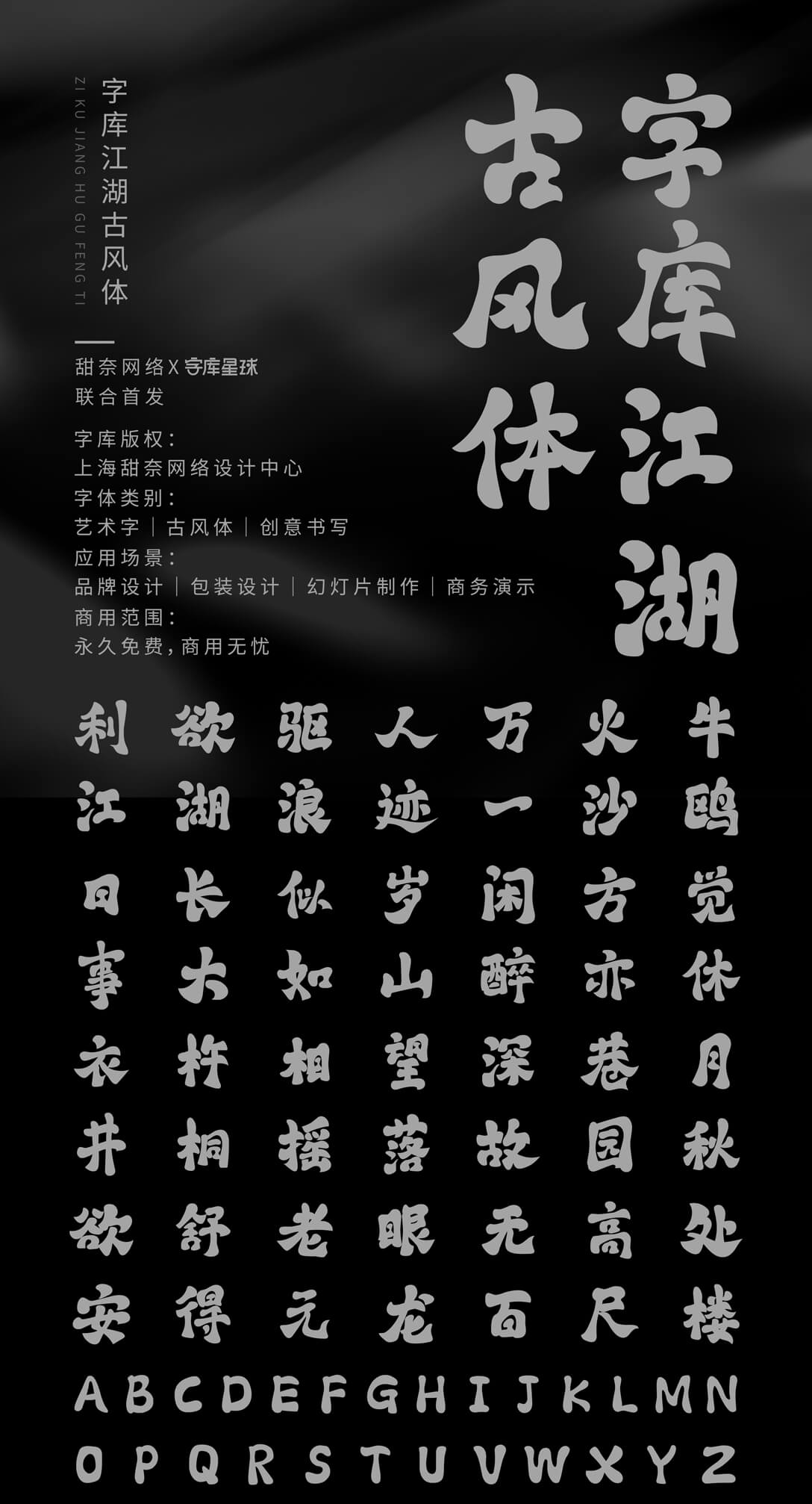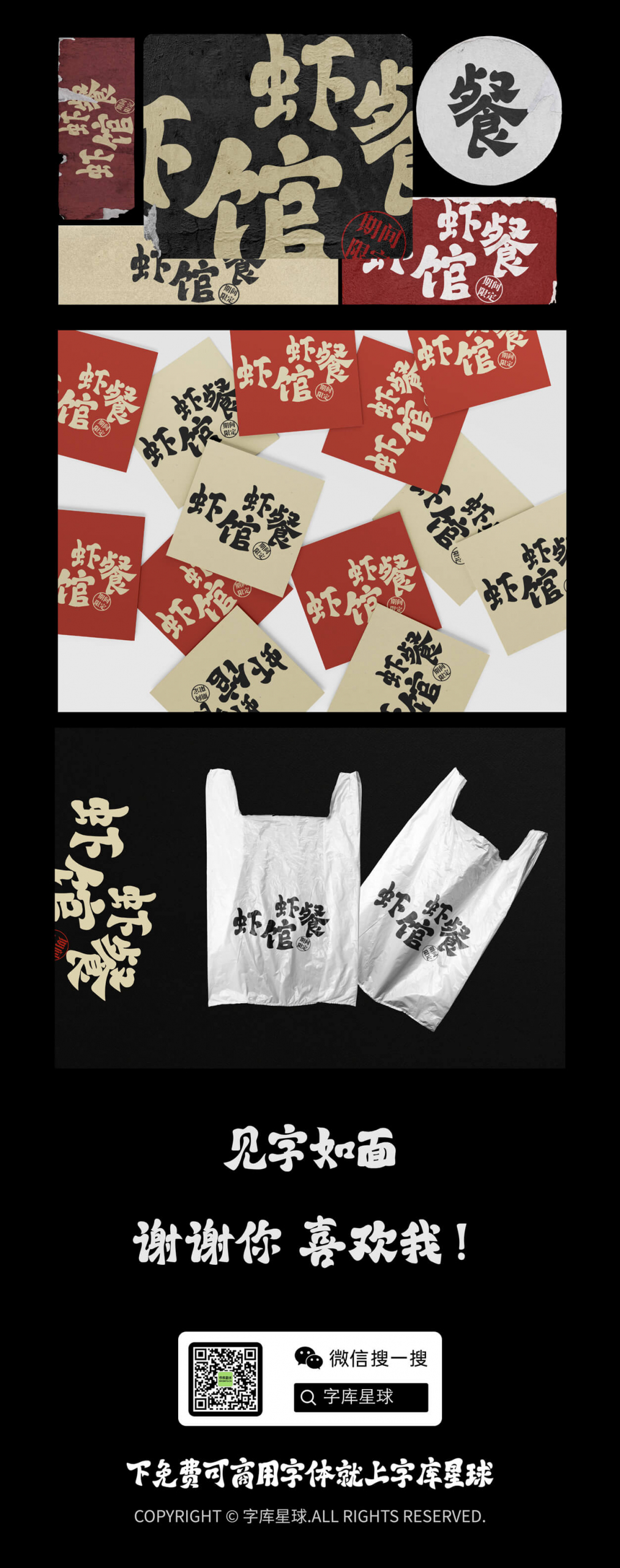
时光飞逝,不知不觉间,字库星球已悄然走过一年的旅程。身为设计师,想必大家的字库都囤积了琳琅满目的字体,可真正派上用场的却寥寥无几。首当其冲的便是恼人的字体侵权难题,在各大设计师交流群里,“某某字体能不能免费商用” 几乎成了高频问题。对于品牌设计师而言,这更是一道 “紧箍咒”,稍不留意,使用了版权受限字体,品牌产品就得面临全网下架的尴尬局面,心血付诸东流。
再者,设计潮流的更迭犹如白驹过隙,令人目不暇接。虽说当下免费的高品质中文字体层出不穷,可客户与老板的审美和需求愈发刁钻多变,现有的字体库渐渐难以招架,难以填满大家愈发高涨的创作欲壑。
好在,新年伊始,一份专属惊喜已为各位设计师备好!甜奈网络与字库星球携手联合首发,推出一款为餐饮品牌量身打造的拙字 —— 字库江湖古风体。
“字库江湖古风体 常规”是一款书写很新颖的字体,字体大方,适合各种设计作品使用!欢迎下载!